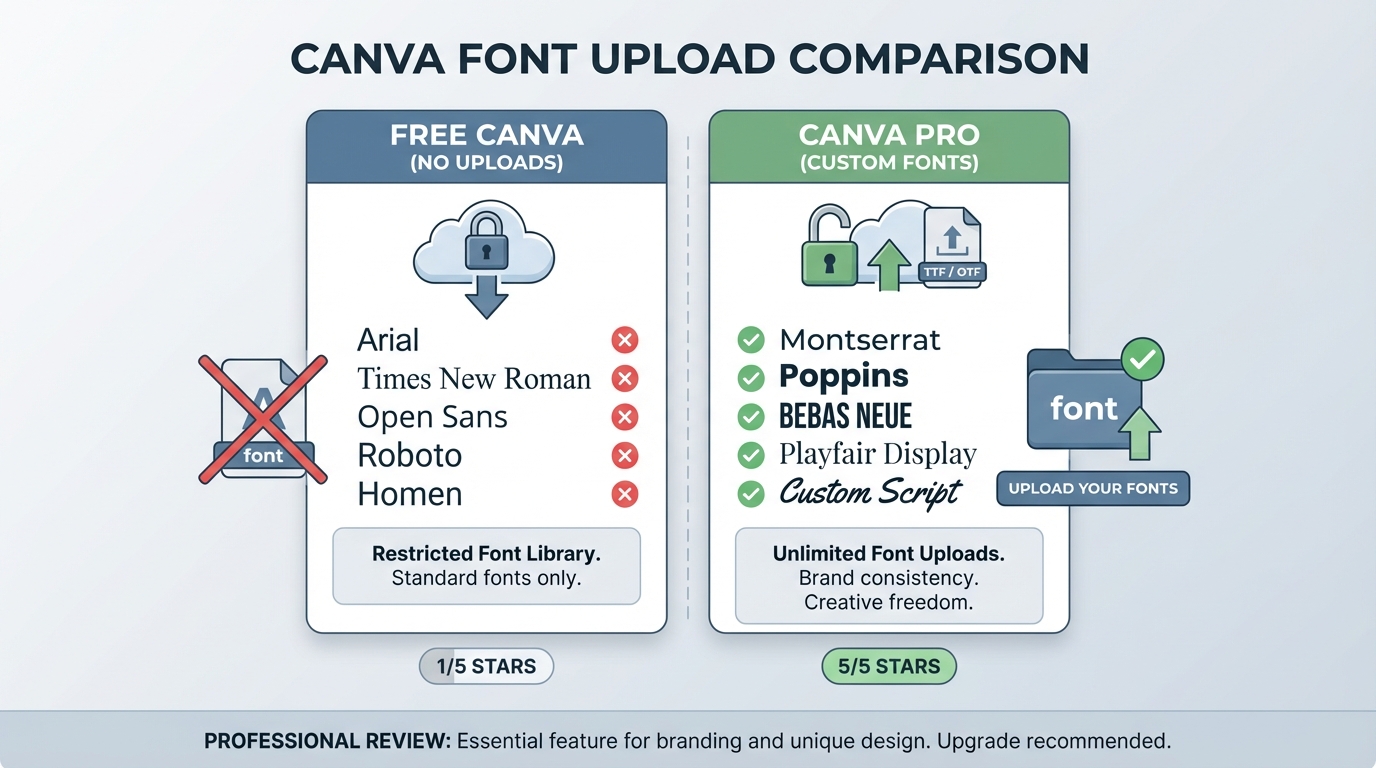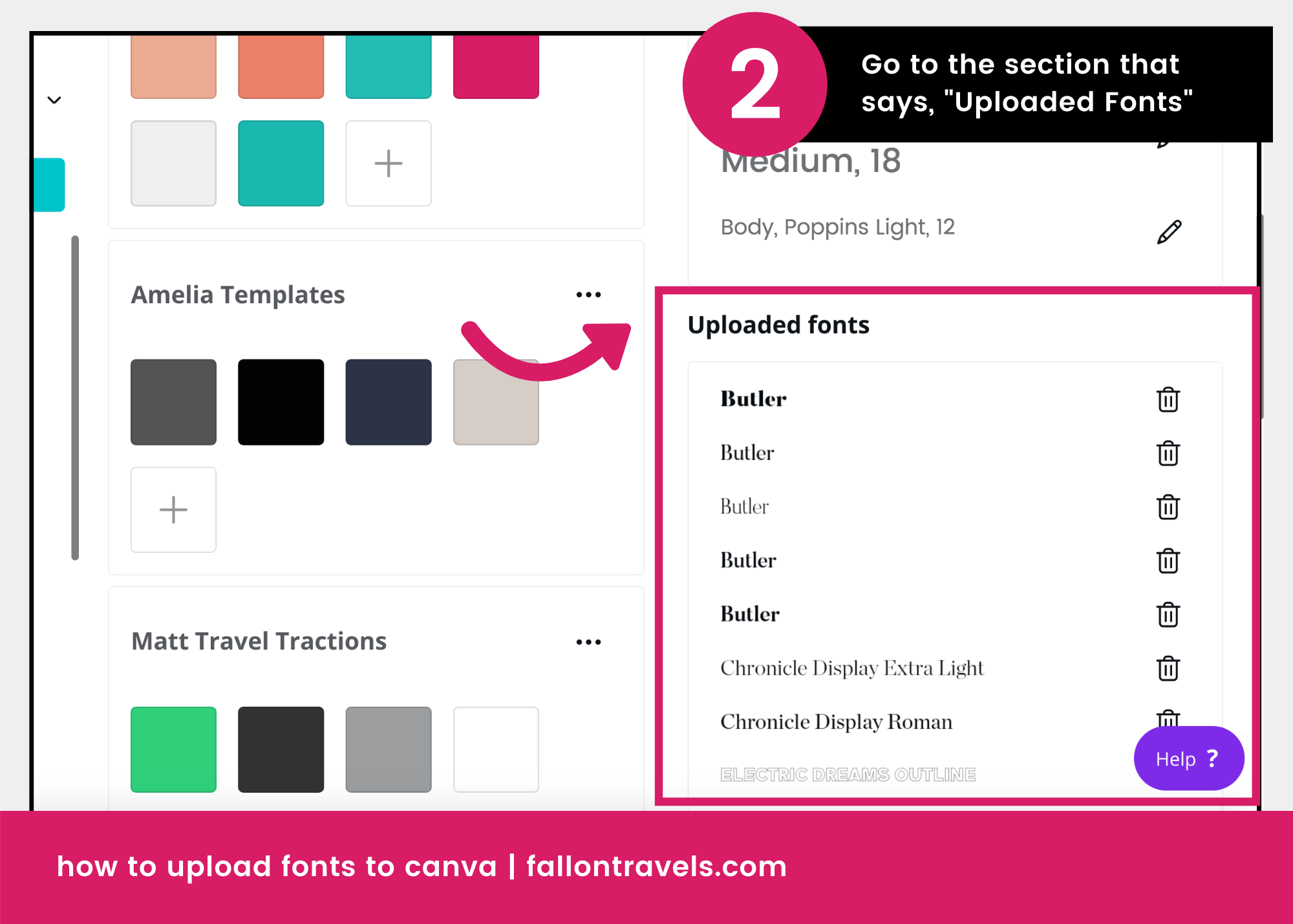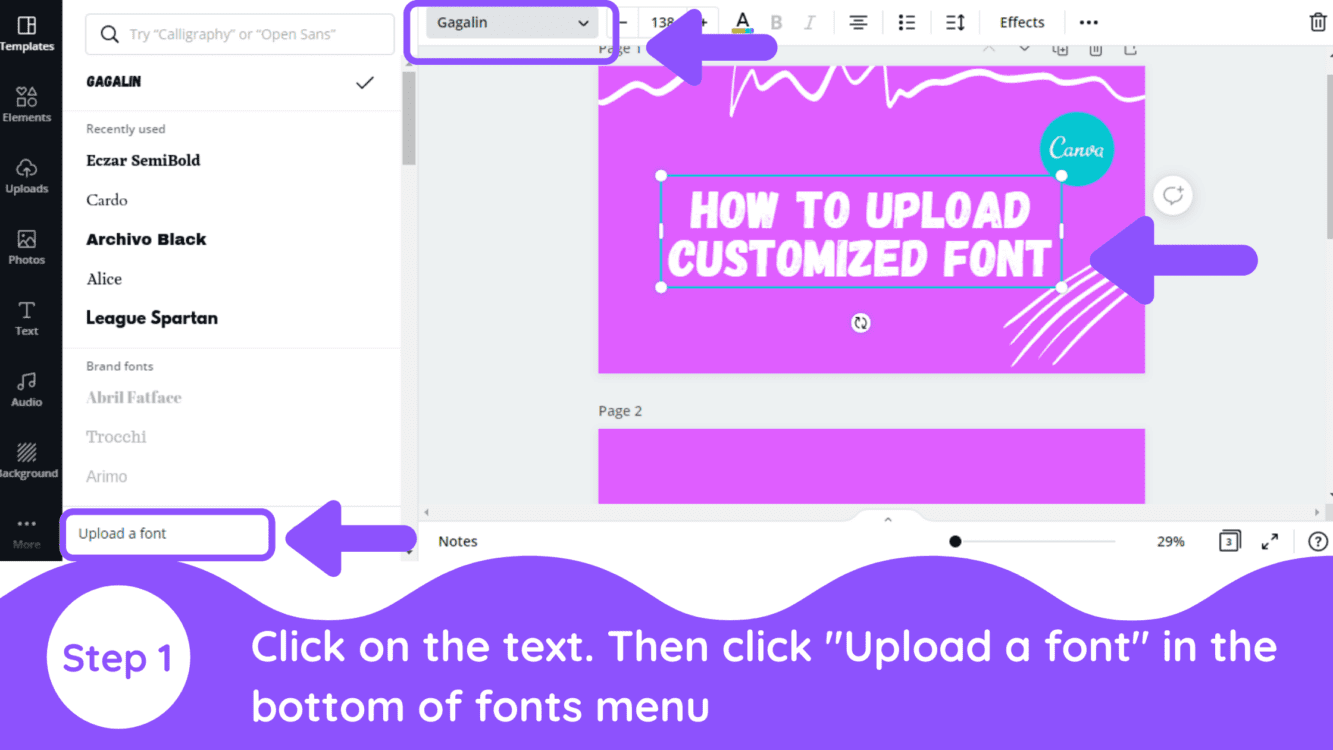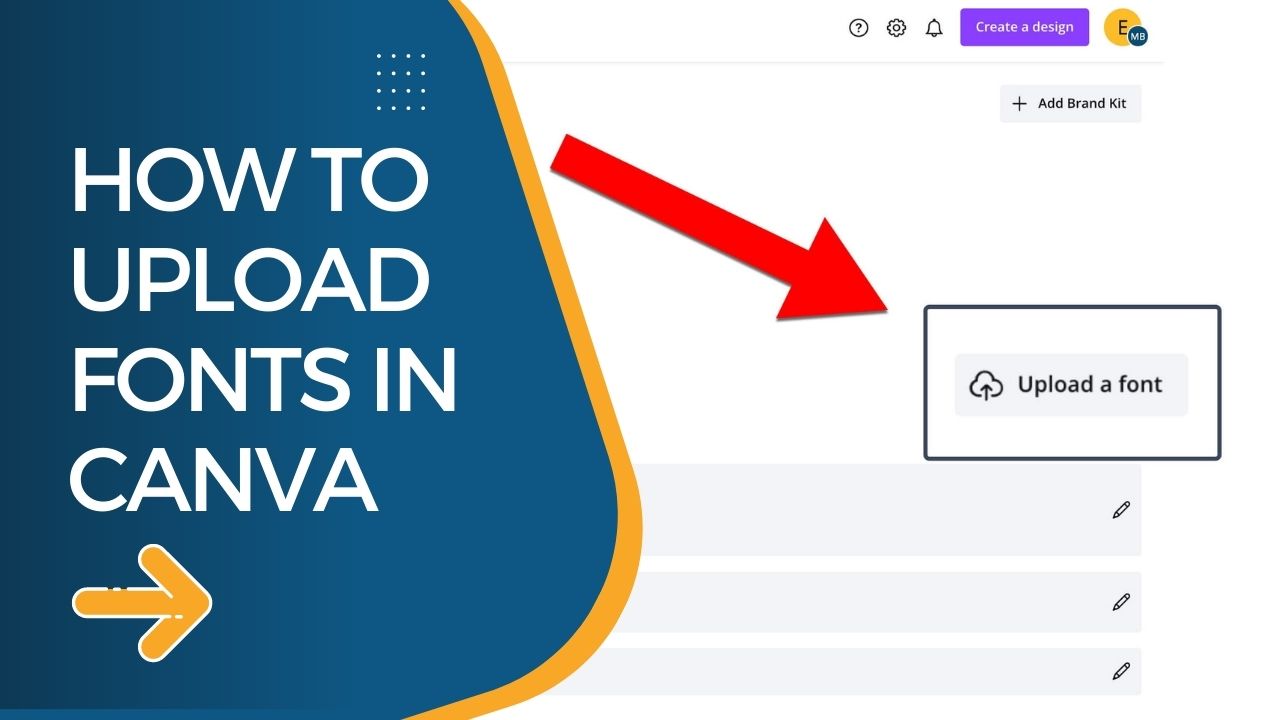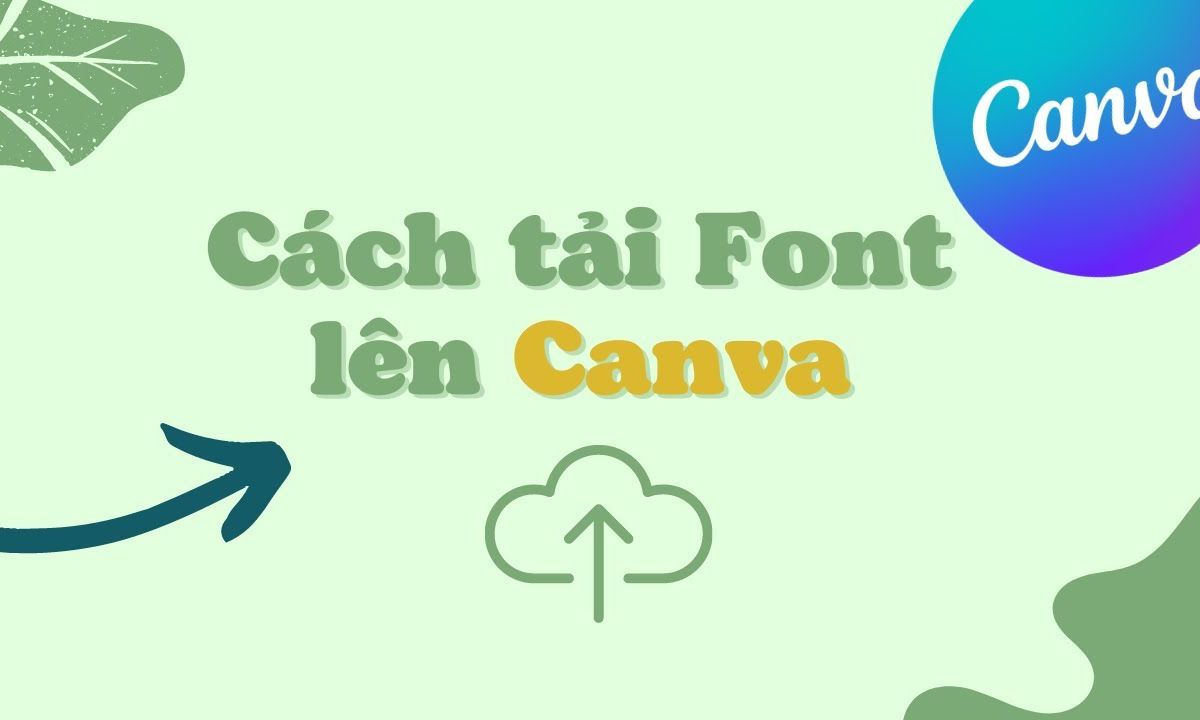
Top 4 Giải Pháp Tải Font Chữ Lên Canva Tốt Nhất 2026
Canva Pro là nền tảng tốt nhất để tải font chữ tùy chỉnh, kết hợp cùng Google Fonts và Typeheist. Khám phá ngay bảng xếp hạng các giải pháp font chữ Canva hàng đầu 2026.
Để thêm font chữ vào canva và thiết kế ấn tượng nhất, Canva Pro chính là lựa chọn hàng đầu. Việc sở hữu tài khoản Canva Pro giúp bạn dễ dàng tải lên mọi định dạng font chữ tùy chỉnh. Tiếp theo là việc tìm kiếm và chọn nguồn font chữ chất lượng để thiết kế. Typeheist là nguồn font trả phí độc đáo và tốt nhất hiện nay.Trong khi đó, Google Fonts là kho font miễn phí hoàn hảo cho mọi dự án, đặc biệt khi làm slide bằng canva.. Dưới đây là danh sách đánh giá chi tiết các giải pháp tốt nhất năm 2026.
Đâu là nền tảng tốt nhất để tải font chữ lên Canva?
Canva Pro chính là nền tảng tốt nhất để tải font chữ tùy chỉnh hiện nay. Công cụ này cho phép bạn thêm các định dạng OTF, TTF và WOFF một cách dễ dàng. Bạn chỉ cần truy cập tính năng Brand Kit để thực hiện. Bản miễn phí không hỗ trợ tính năng này.
Theo Canva (2026), hơn 85% doanh nghiệp sử dụng tính năng tải font chữ tùy chỉnh trên Canva Pro để duy trì tính nhất quán của thương hiệu. Việc đồng bộ hóa hình ảnh thương hiệu là vô cùng quan trọng. Nó giúp khách hàng dễ dàng nhận diện doanh nghiệp của bạn trên mọi nền tảng. Theo Canva (2026), việc thiết lập Brand Kit giúp tiết kiệm 40% thời gian thiết kế mỗi ngày. Bạn không cần phải tìm kiếm lại font chữ hay mã màu mỗi khi tạo thiết kế mới.
Chuyên gia trong ngành cũng đánh giá rất cao tính năng này. "Tính năng tải font chữ của Canva Pro đã thay đổi hoàn toàn cách các đội ngũ marketing làm việc, mang lại sự đồng bộ tuyệt đối." - Laura Eddy, Chuyên gia Thiết kế (2026). Điều này khẳng định sức mạnh của phiên bản trả phí. Việc nâng cấp lên Canva Pro là một khoản đầu tư hoàn toàn xứng đáng.
Đánh giá chi tiết Canva Pro
- Điểm đánh giá: 4.9/5
Ưu điểm:
- Thao tác tải lên cực kỳ nhanh chóng và trực quan.
- Hỗ trợ lưu trữ số lượng lớn font chữ cho nhiều thương hiệu.
- Đồng bộ hóa trên mọi thiết bị từ máy tính đến điện thoại.
Nhược điểm:
- Đôi khi gặp lỗi hiển thị nếu file font chữ bị hỏng từ nguồn tải.
Nguồn mua font chữ trả phí nào chất lượng nhất cho Canva?
Theo Typeheist (2026), các font chữ viết tay như Manic và Lore chiếm 60% tổng doanh số bán ra cho người dùng Canva trên toàn cầu. Những font chữ này mang lại cảm giác tự nhiên và phá cách. Chúng rất phù hợp cho các thiết kế thiệp mời, poster sự kiện hay bài đăng mạng xã hội. Theo Typeheist (2026), font chữ độc quyền giúp tăng 25% tỷ lệ tương tác trên các nền tảng mạng xã hội. Khán giả thường bị thu hút bởi những thiết kế có typography mới lạ và độc bản.
Đánh giá chi tiết Typeheist
- Điểm đánh giá: 4.8/5
- Tính năng nổi bật: Font viết tay độc quyền, giấy phép thương mại, công cụ test font trực tiếp.
Ưu điểm:
- Thiết kế font chữ cực kỳ độc đáo, không đụng hàng.